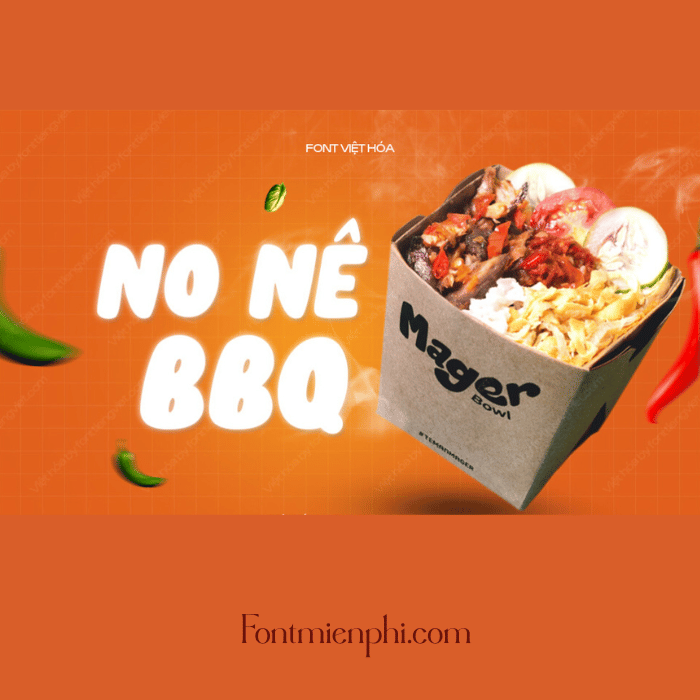
Font Việt hóa 1FTV VIP Unicorn Pop – Nét chữ độc đáo, sáng tạo không giới hạn
Font Việt hóa 1FTV VIP Unicorn Pop là bộ font chữ nghệ thuật với phong cách dễ thương, bắt mắt, lấy cảm hứng từ thế giới kỳ ảo của những chú kỳ lân. Được thiết kế độc quyền dành cho thành viên VIP, font chữ này phù hợp với các dự án thiết kế đồ họa, poster, card mời, logo, hoặc nội dung mạng xã hội cần sự sinh động, trẻ trung.
✔ Nét chữ bo tròn, mềm mại – Tạo điểm nhấn ấn tượng cho thiết kế.
✔ Đa dạng kiểu chữ – Dễ dàng kết hợp với nhiều phong cách khác nhau.